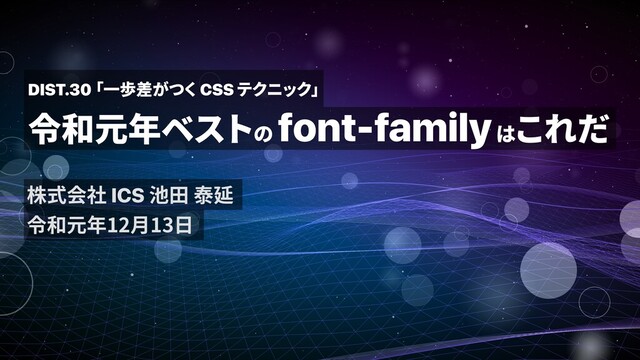
令和元年ベストのfont-familyはこれだ / Better font-family 2019 in Japanese
OSやブラウザのアップデートによりウェブサイトのフォントは影響を受けてきました。最近だとiOS 13 Safariでフォントが激太りを起こしたり、macOS CatalinaとChromeの組み合わせで明朝体化するウェブサイトが多発しました。
他にも「MS Pゴシック」の呪縛、「游ゴシック」の薄さ問題、アンチエイリアスの変化など問題はつきません。このライトニングトークでは、現代の最適解としてのフォント指定を紹介します。
Website fonts have been affected by OS and Browser updates. Recently, iOS 13.0 Safari has caused a lot of fonts problems, and there have been many websites that appear serif fonts in macOS Catalina and Chrome.
There are other problems such as “MS P Gothic” , “Yu Gothic” thinness problems, and antialias fonts changes. In this Lightning Talk, we will introduce font specification as the optimal solution for today.
1. /* ⽇本語指定 */ font-family: -apple-system, BlinkMacSystemFont, "Segoe UI", "Hiragino Sans",
"Hiragino Kaku Gothic ProN", Meiryo, sans-serif; /* ボールド指定 */ font-weight: 600;
2. OS
3. 2017 Windows Chrome 56 Firefox 57 sans-serif 2017 1 (Chrome)
2017 8 (Firefox) sans-serif sans-serif
4. UI Windows 10 : Yu Gothic UI Windows 8.1 :
Segoe UI Meiryo font-family: system-ui
5. : /* ⽇本語指定 */ font-family: -apple-system, BlinkMacSystemFont, "Segoe UI", "Hiragino
Sans", "Hiragino Kaku Gothic ProN", Meiryo, sans-serif; /* ボールド指定 */ font-weight: 600;
6. Hiragino Sans /* ⽇本語指定 */ font-family: -apple-system, BlinkMacSystemFont,
"Segoe UI", "Hiragino Sans", "Hiragino Kaku Gothic ProN", Meiryo, sans-serif; /* ボールド指定 */ font-weight: 600;
7. iOS 13 Safari sans-serif Hiragino Sans iOS Hiragino Sans W3,
W6, W8 font-weight: bold; 700 Hiragino Sans W8
8. font-weight: 600; /* ⽇本語指定 */ font-family: -apple-system, BlinkMacSystemFont, "Segoe UI",
"Hiragino Sans", "Hiragino Kaku Gothic ProN", Meiryo, sans-serif; /* ボールド指定 */ font-weight: 600; iOS 13.1 W8 W7
9. BlinkMacSystemFont SF Display Pro Hiragino Sans macOS Hiragino Sans (100
900) font-weight: 600; macOS Catalina × Chrome 79